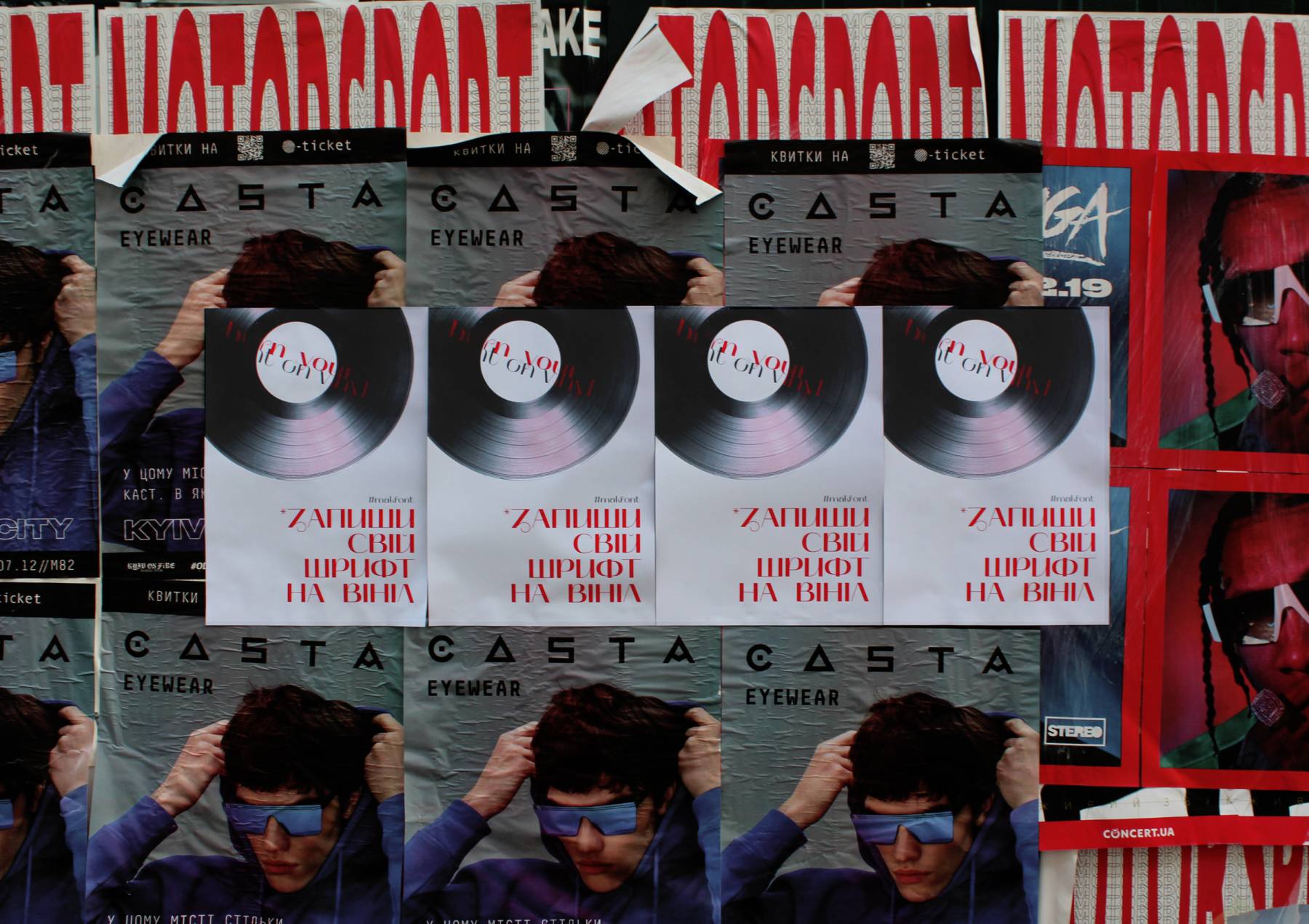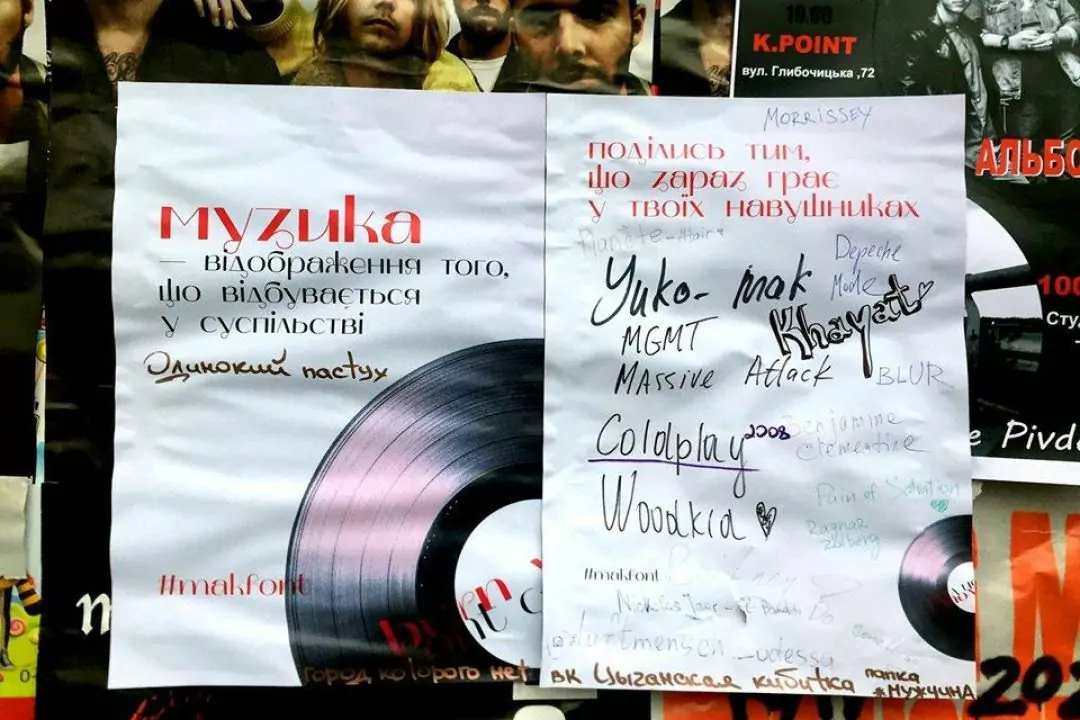
Дизайнер створив шрифт, натхненний сучасною українською музикою
Український дизайнер Валентин Ткаченко створив контрастний шрифт Mak. На його створення автора надихнула українська музика з сучасним експериментальним звучанням народних мотивів.
Валентин Ткаченко – графічний дизайнер, який вчиться на курсі Visual Communication Professium у Projector. У рамках цього курсу він створив український шрифт.
«Мак – це новий акцидентний шрифт з українським характером, натхненний сучасною українською музикою. Якщо конкретно – це Yuko, ДахаБраха, Khayat, Onuka, Аліна Паш, вони створюють просто неймовірну музику, експериментуючи з етнічними мотивами, які в підсумку звучать зовсім не архаїчно, а модерно», – каже Валентин.
Основою в створенні шрифту став принцип експериментів з етнікою – історичними формами, контрастністю, сміливими конструкціями, які створюють новий образ української кирилиці.